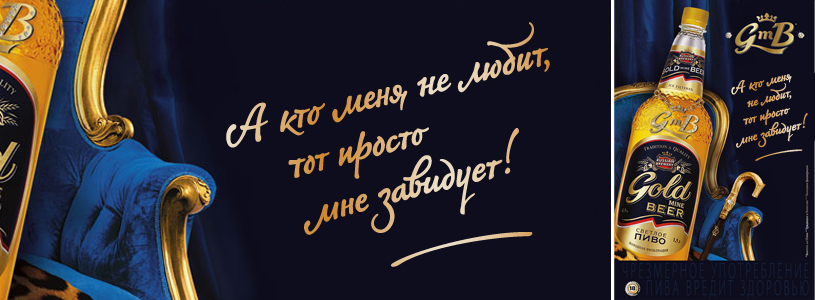
Golden Mine Beer
Каллиграфия по заказу рекламного агентства «Родная Речь». Слоган для принтов пива Gold Mine Beer. По технике — свободное письмо кистью, по стилю — дешёвый гламур. Уверенная подпись с несколькими разудалыми буквами.